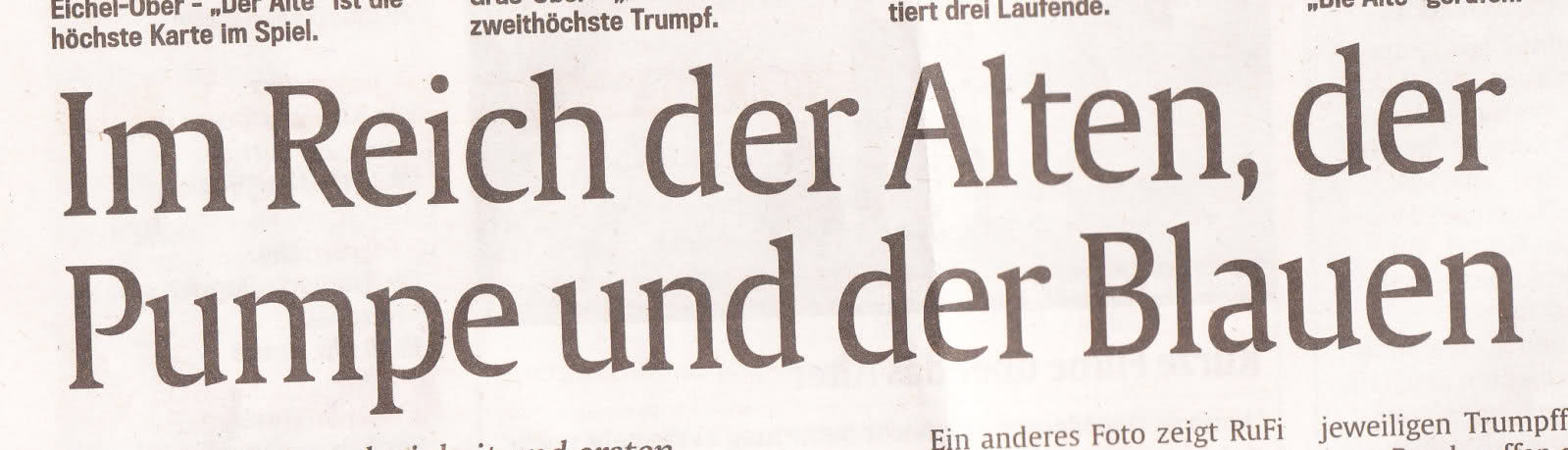
Wird in dem Beiblatt der Abendzeitung "Die Stadt" verwendet, und hier wird sogar auf das neue Erscheinungsbild (mit Info zur "exklusiven Gulliver") hingewiesen.
ungers letzte schriften sind alles typische zeitungs-schriften, sonst sieht man sie eher selten.
die sächsische zeitung verwendet seit einiger zeit auch die swift und hat dafür die schöne
ff zine abgewählt, warum auch immer. ich finde viele der unger schriften nicht so ansprechend
an irgendetwas stoße ich mich da immer. ist aber auch gewöhnungssache, sie sind halt sehr
eigen. nicht hässlich oder so sondern sehr speziell.
Ist wohl auch Geschmackssache. Mir gefällt der ihm eigene Duktus sehr gut (natürlich nicht für alles und ständig, aber so grundsätzlich). Aber einen ganz eigenen Stil (mit hohem Wiedererkennungswert) hat der Mann auf jeden Fall – ich hab die Gulliver hier auch nur über den Umweg «lustige n-Punzen» -> Swift -> Unger -> Gulliver gefunden.
bei der gulliver mag ich komischerweise den spitzen Anstrich beim a, im Gegensatz zur Slimbach.
Magst Du das von der Constantia? Ist auch eher spitz. (Ich finds toll :biglove: )
Bei der Slimbach ists vielleicht etwas übertrieben? Piekst ein bisschen sehr.
Geschmackssache sicher – das komische ist nur immer, dass diese – sagen wir mal vorsichtig – »Eigenheiten« der Unger-Schriften auch noch als lesefördernd verkauft werden. Ich hab mich gerade letztens erst wieder wegen der Unger-Schrift mit großer Mühe durch sein Buch »While you’re Reading« gequält. Und in dem Buch geht es ja schließlich auch noch ausschließlich um Lesbarkeit!
Nicht dass die Schriften keine gestalterischen Reiz hätten, aber die Fließtexttauglichkeit in Büchern und Zeitungen würde ich doch sehr in Frage stellen.
ja, das sehe ich auch so. ich finde sie für den fließtext viel zu außergewöhnlich. als headlineschrift in größeren graden haben die schriften sicher mehr berechtigung.
jedoch finde ich auch das gerade die eigenheiten der schriften in den kleinen graden untergehen, sie verlieren an charakter. gerade bei der sächsischen zeitung sieht man das gut – die ff zine hatte stil, einen eigenen charakter durch den wechsel zur swift sieht nun alles nach einheitsbrei aus, geradezu langweilig.